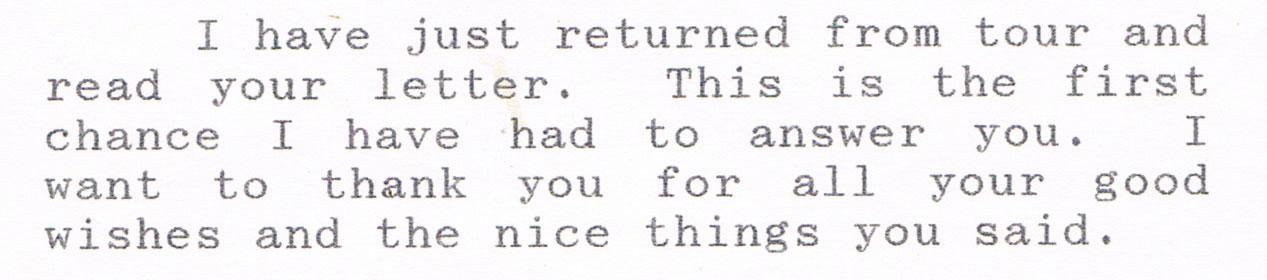
Suche diese (vermutlich) Schreibmaschinen- oder Computerschrift aus den späten 1980ern
Rein Interesse halber wüsste ich, ob jemand diese Schriftart benennen kann oder eine ähnliche Schriftart kennt.
Zum Hintergrund: Die Schriftart wurde von einem Sekretariat einer US-amerikanischen Sängerin im Jahr 1989 verwendet. Der Brief sieht aus, als sei er mit einer Schreibmaschine getippt worden, allerdings ist er im Blocksatz verfasst, sodass ich fast denke, es könnte ein Computerausdruck sein.
Hat eventuell jemand eine Idee?
Ich dachte auch als erstes an die Courier, allerdings das "j" und "y" haben eine Art Tropfen unten, den die Courier nicht aufweist.
Ich habe auch was ähnliches gefunden ... Century Schoolbook Monospaced ... Bookface ist Schoolbook?
Die „späten“ Schreibmaschinen konnten auch Blocksatz.
Der Ausdruck erinnert mich allerdings mehr an meinen alten Star-24-Nadeldrucker.